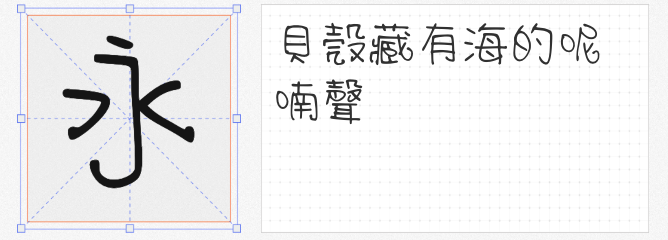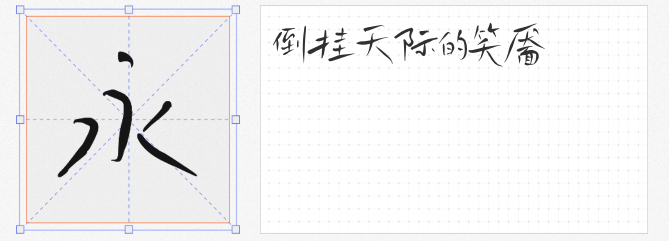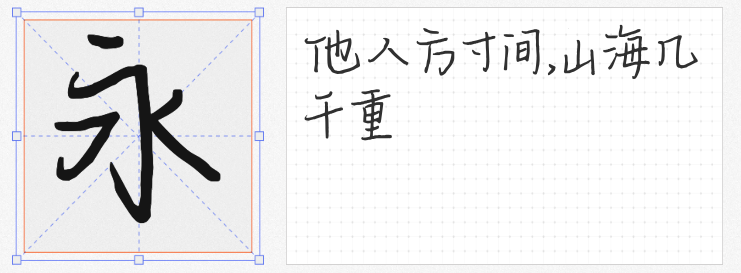
在内容创作中,手写字体的温度感能为画面注入灵魂。今天推荐四款免费商用的高颜值手写字体,涵盖自然随性、工整严谨、艺术纤细等不同风格,轻松适配Vlog封面、Plog排版、社交媒体图文等场景!
由设计师游清松以原子笔手写原稿转化而成,这款字体最大亮点是打破电脑字体的机械感。笔画转折处保留了真实手写的顿挫痕迹,中英文、符号数字全覆盖,无论是电子屏幕阅读还是印刷输出都清晰舒适。推荐用于Vlog字幕、Plog手账体文字,轻松营造“手写笔记”的治愈氛围。
来自云峰字库的这款字体堪称“手写界印刷体”,横平竖直间透着严谨的书写态度。虽为手写风格,但结构匀称、重心稳定,适合需要突出专业感的场景,如知识类Vlog标题、Plog时间轴标注。即使放大查看,每一笔的起收笔细节依然精致耐看。
看似潦草却暗藏巧思,这款字体以“拙中见巧”为特色。笔画粗细自然变化,保留了书写时的飞白效果,辨识度极高且毫无杂乱感。无论是旅行Vlog的标题大字,还是美食Plog的食材标签,都能通过它的洒脱感传递轻松氛围,尤其适合年轻化内容创作。
笔触如行云流水,这款艺术字体以极细线条勾勒出书法韵味,适合追求精致感的设计。无论是网页标题、海报标语,还是书法字帖临摹,它都能用飘逸的笔画传递东方美学。在Plog中用作章节分隔线或装饰性文字,瞬间提升画面格调。